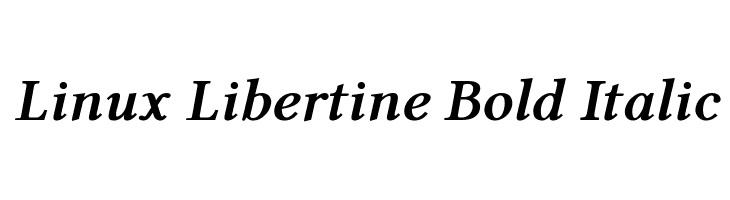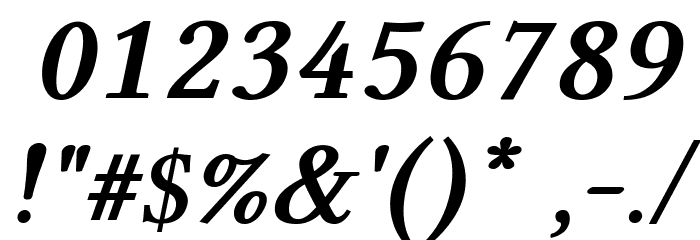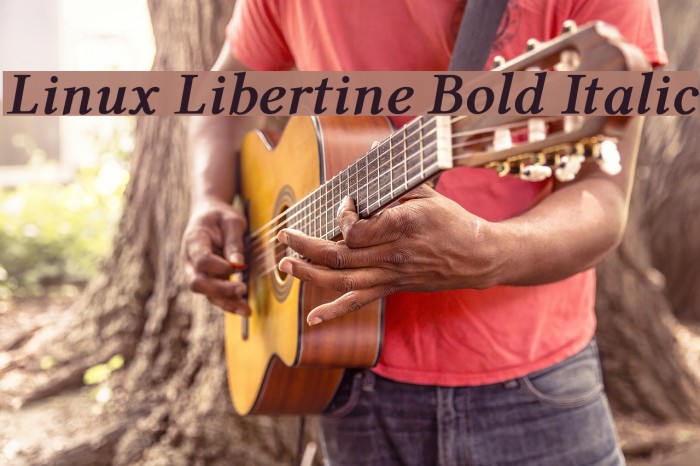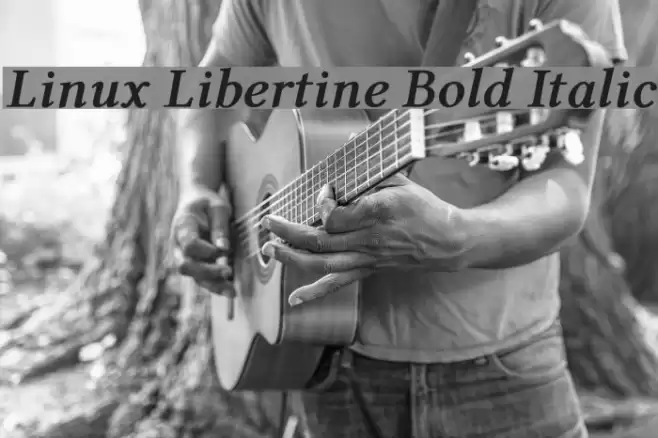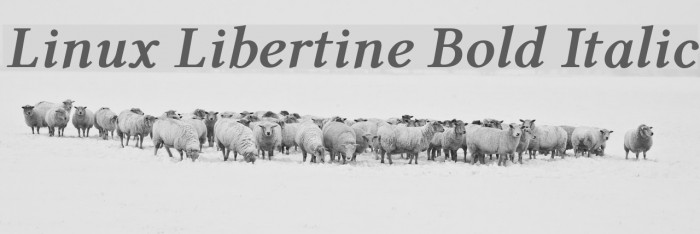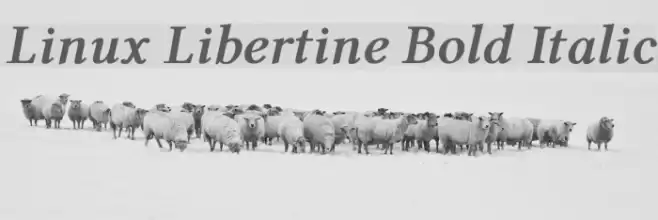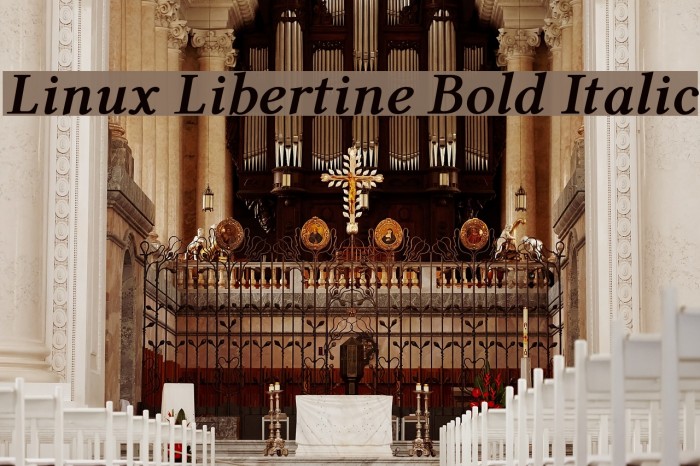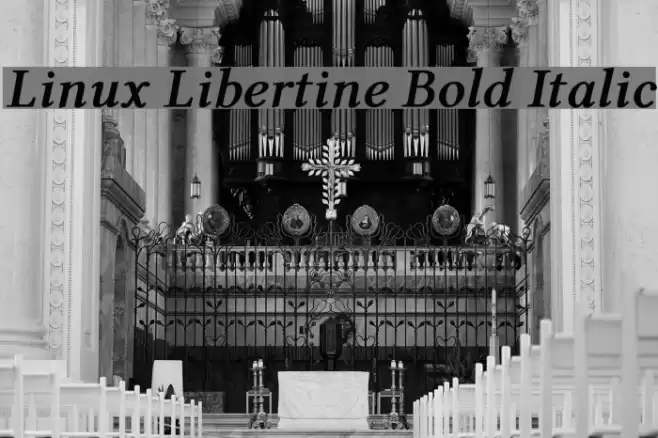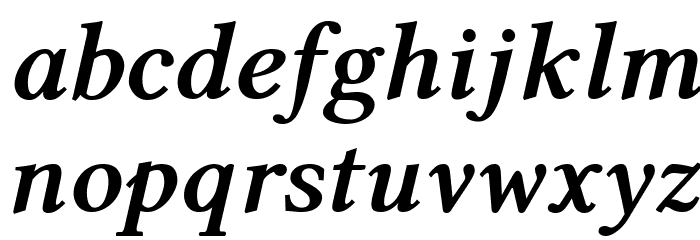
Linux Libertine Bold Italic Font
✎ Serif
| Estilo general | Classic |
| Caso de uso | Headlines, Body text, Logos |
| Proyectos propuestos | Ideal for book covers, editorial design, formal invitations, and branding projects that require a classic yet modern touch. |